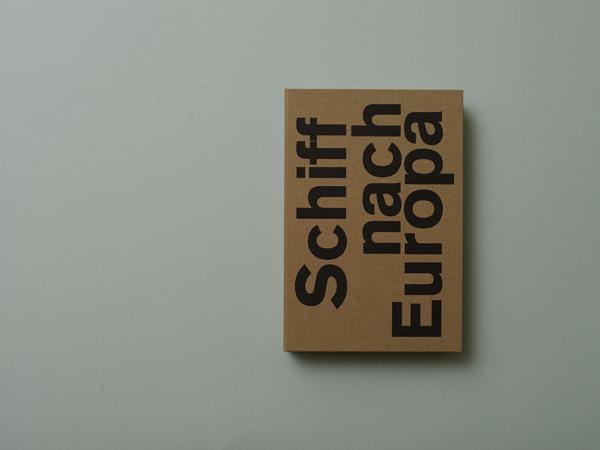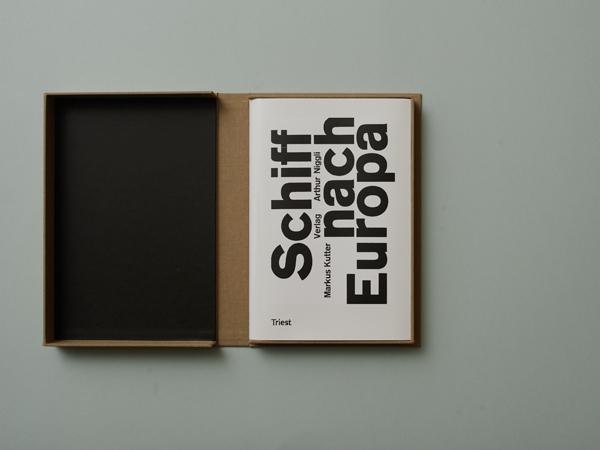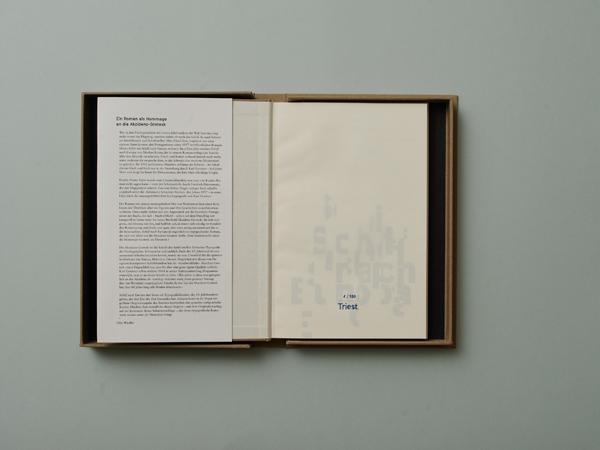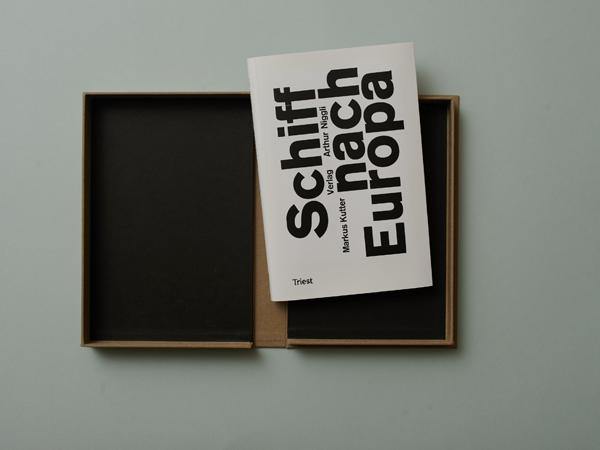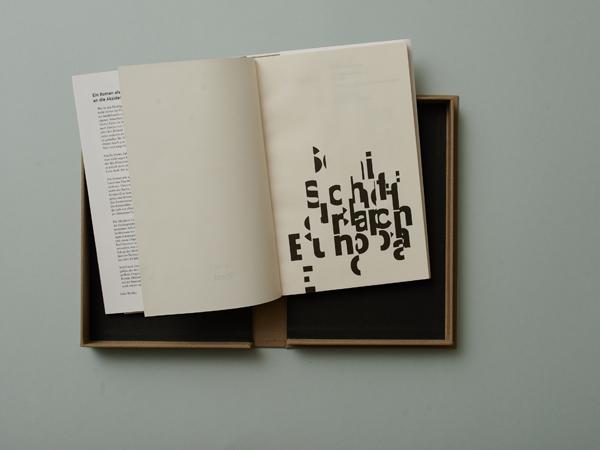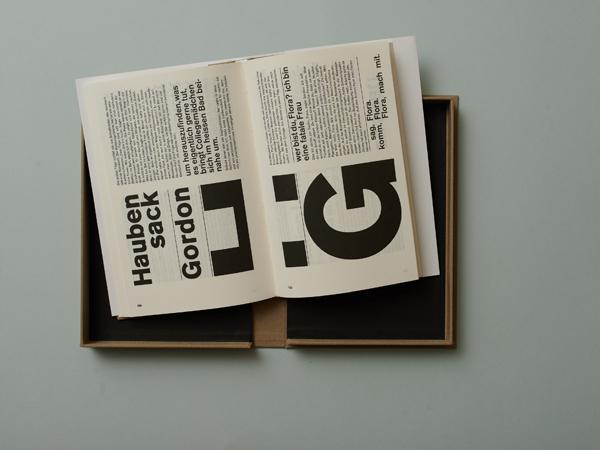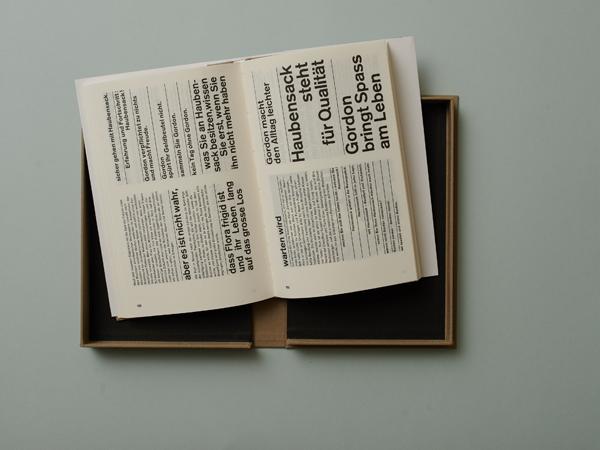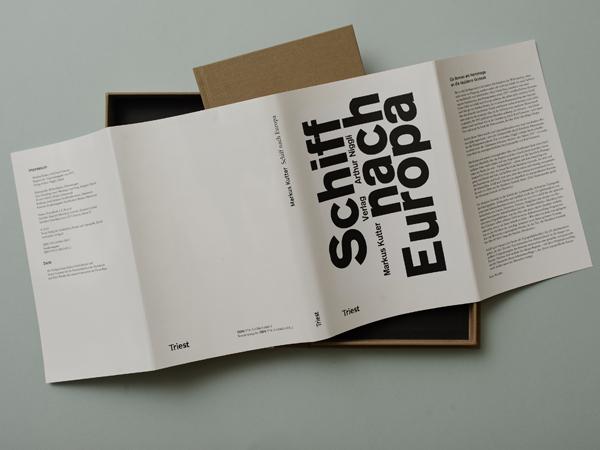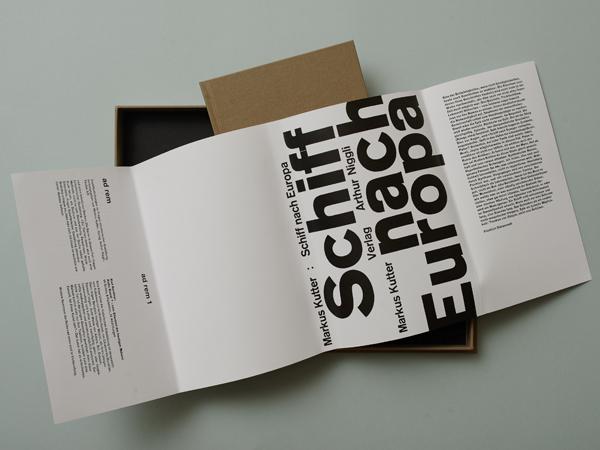
Markus Kutter
Schiff nach Europa
Buchgestaltung: Karl Gerstner
Umschlaggestaltung Reprint: Wessinger und Peng, Stuttgart
Leinenband mit beidseitig bedrucktem Schutzumschlag in einer handgefertigten leinenbezogenen Kassette mit Siebdruck
Markus Kutters Roman Schiff nach Europa – «optisch organisiert» von Karl Gerstner – «nimmt früh eine experimentelle Position ein, die in der Buchgestaltung erst einige Jahre später zum Durchbruch gelangen wird», schrieb François Rappo. Es ist durch seine auf den Text abgestimmte Typografie als Meilenstein der Schweizer Buchgestaltung anzusehen und wurde 1957 als Schönstes Schweizer Buch ausgezeichnet.
Der als synthetischer Roman bezeichnete Inhalt (eine Schiffspassage von New York nach Europa auf der später gesunkenen Andrea Doria) besteht aus verschiedenen Textsorten – Erzählung, Drama, Gespräch und Monolog. Markus Kutter stellte sich bereits beim Schreiben vor, dass der Text typografisch entsprechend inszeniert werden müsste. Karls Gerstner beschrieb diese Aufgabe als «persönliches Experiment» und «besondere Delikatesse.»
Die Freude, «integrale Typographie» umgesetzt zu haben, ist dem Buch anzumerken und springt auf die Leser über.
Das Buch ist seit Jahren vergriffen und von Sammlern gesucht. Durch die Neuauflage wird es vielen erstmals möglich sein, das Kultbuch endlich selbst in den Händen zu halten. Der Reprint ist originalgetreu, ein beidseitig bedruckter Schutzumschlag liefert sowohl das ursprüngliche Cover als auch die aktualisierte Version mit einem Kommentar von Felix Wiedler.
Über den Autor
Markus Kutter (1925–2005) war als Autor und Publizist sowie als Historiker und Politiker tätig. Noch vor seiner Dissertation (1954) begann er als Redakteur der Basler Chemiefirma Geigy, deren Kommunikationsabteilung er aufbaute und bis 1958 leitete.
1959 gründete er mit Karl Gerstner die Werbeagentur Gerstner + Kutter, ab 1962 GGK (mit Paul Grediger als Gerstner, Grediger + Kutter), die mit ihren Kampagnen weltweit für Aufsehen sorgte.
Als Publizist und Sachbuchautor trat er bereits 1955 in Erscheinung – zusammen mit Max Frisch und Lucius Burckhardt (und Karl Gerstner als Gestalter) veröffentlichte er «achtung: die Schweiz». Das Manifest schlägt vor, auf die Landesausstellung 1964 zu verzichten und stattdessen eine Musterstadt zu bauen, blieb aber Utopie.
Kutter verfasste zahlreiche Werke, die sich mit Werbung, Gesellschaft und der Basler Geschichte auseinandersetzen. Ausserdem war er politisch im Kanton Basel-Stadt tätig, von 1992–1997 hatte er einen Sitz im Grossen Rat.